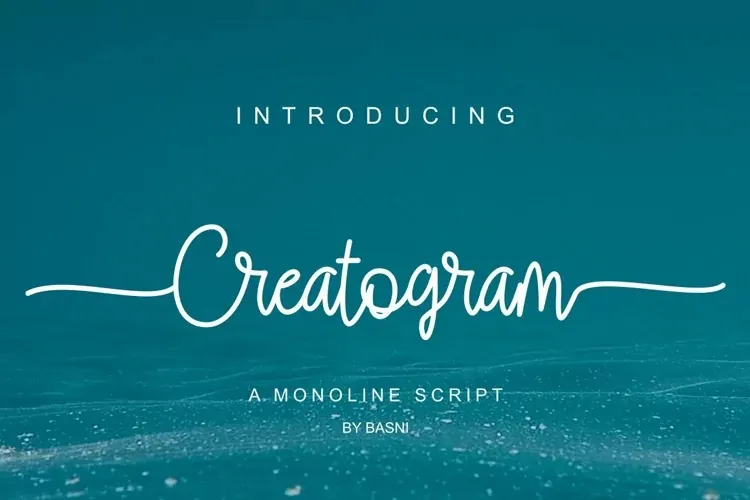
Creatogram Font – Fonte Grátis
Creatogram Font
Esta fonte criada por Basnistd é uma elegante e suave tipografia monoline que transmite delicadeza e naturalidade. Com seu traço fino e escrita à mão, a Creatogram pode transformar qualquer design de marca, site, rótulos de vinho e editorial num trabalho perfeito. O conjunto completo inclui todas as letras maiúsculas e minúsculas, suporte multilíngue, pontuação e swashes tanto no início quanto no final dos caracteres, tudo isso disponível para acesso através de softwares que suportam OpenType. Com essa fonte em sua coleção, pode-se não só criar um design mais arrojado, mas também aprimorar qualquer projeto editorial ou digital que você estiver desenvolvendo.